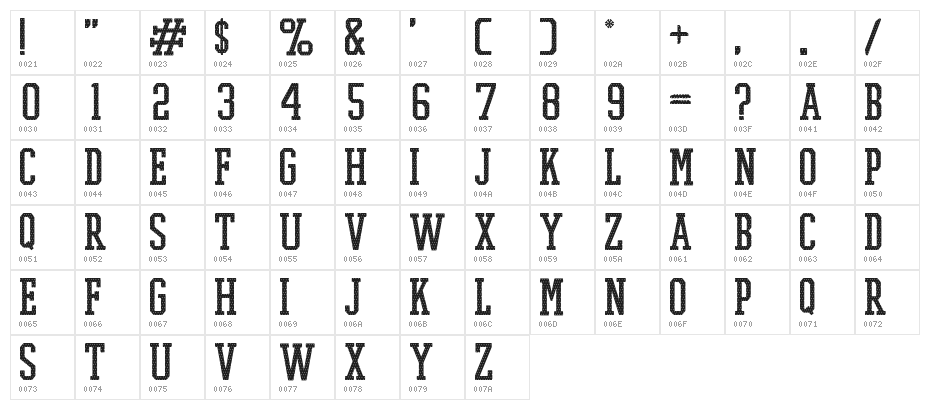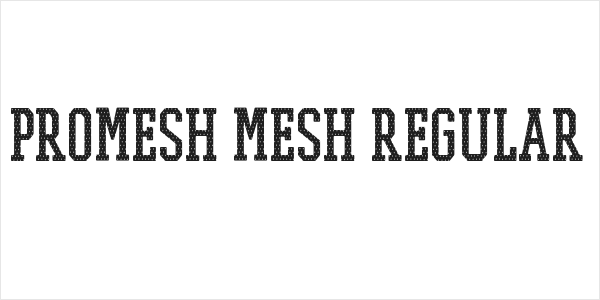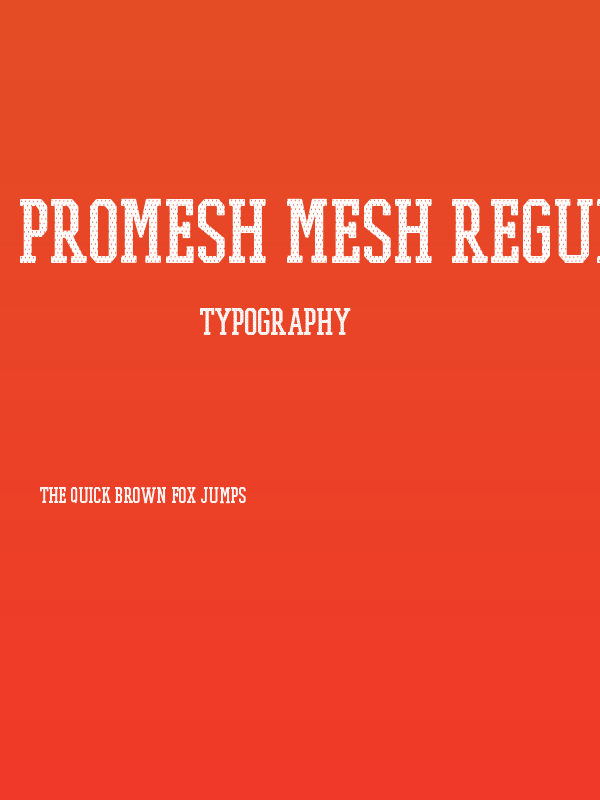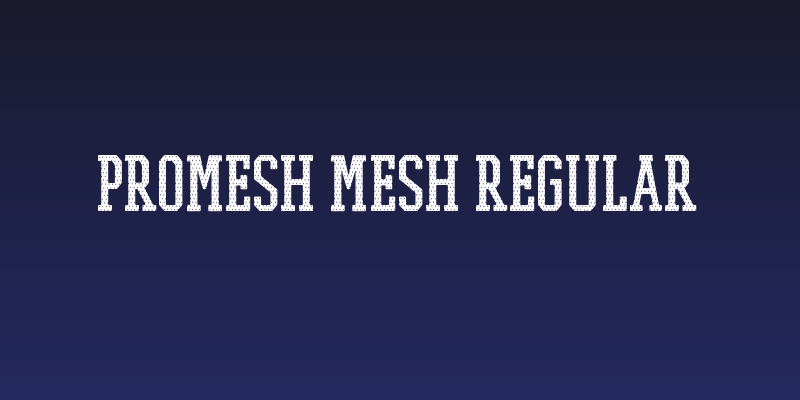
PROMESH Mesh Regular Font
| Progetti proposti | This font is perfect for sports team branding, athletic event posters, merchandise design, and any project requiring a dynamic and energetic feel. |